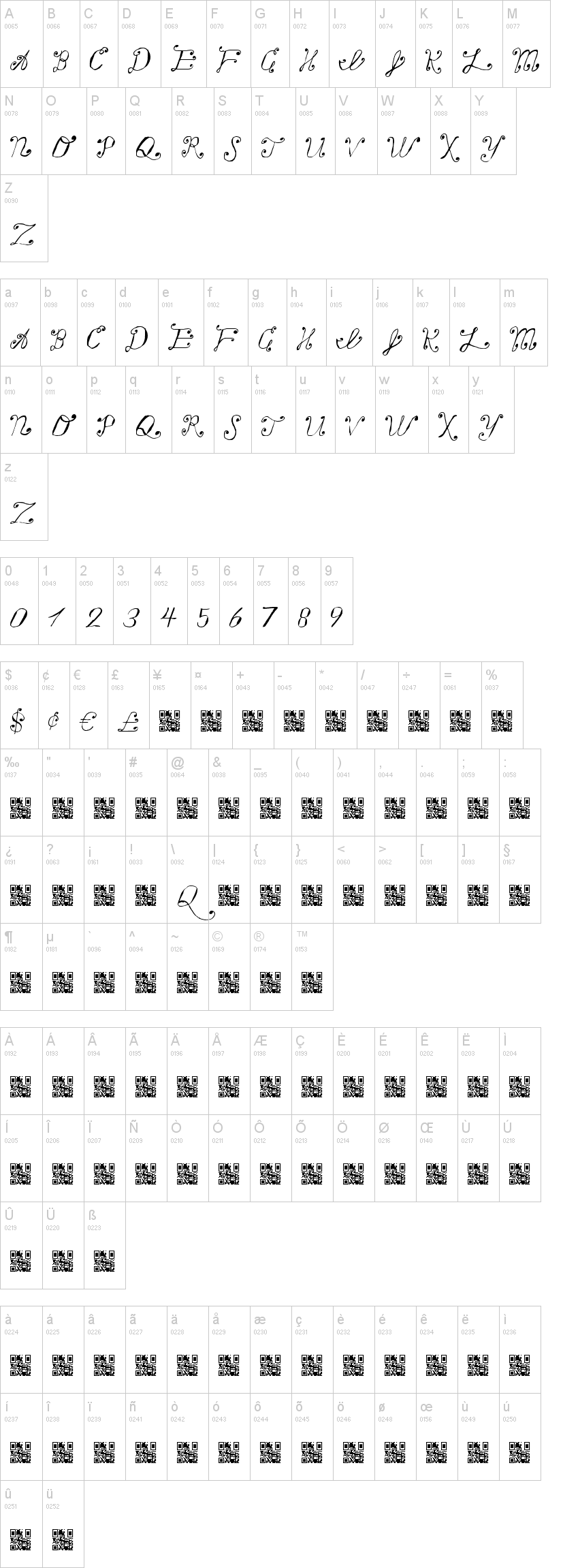
Making a List Checking it Twice
Making a List Checking it Twice 是一种字体,其设计灵感来源于圣诞老人制作圣诞礼物的传统。这种字体采用了圆润、流畅的笔画,给人一种温馨、欢乐的感觉。字母的上下部分采用了不同的线条宽度,使得字体看起来更加有趣,同时也增加了可读性。Making a List Checking it Twice 字体适用于各种场合,尤其适合圣诞节相关的设计,如明信片、海报、宣传册等。
Making a List Checking it Twice是一款非常不错的手写艺术字体,具有很好的视觉感,适合于文化类的宣传设计、商业类品牌的广告和产品包装设计以及个性化文字排版等较多场景。